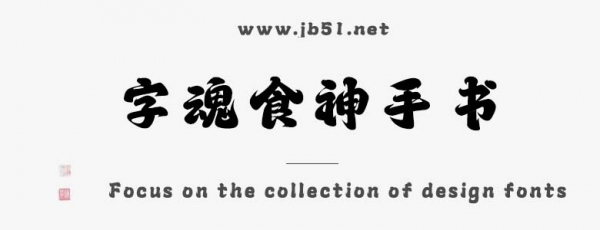
字魂食神手書是由字魂字庫推出的創(chuàng)意字體,該包含9503個中文、字母、 符號和數(shù)字,具有力量的風(fēng)格,可以滿足您設(shè)計上的各種需求,適合應(yīng)用于藝術(shù)設(shè)計、平面宣傳設(shè)計、網(wǎng)頁設(shè)計,書法字帖等領(lǐng)域。
字魂食神手書字體是一款商用的創(chuàng)意書寫字體,該字體包含9503個中文、字母、 符號和數(shù)字,具有力量的風(fēng)格,可以滿足您設(shè)計上的各種需求,該字體主要用于標題等場景, 您不但可以在字魂網(wǎng)下載字魂食神手書字體,同時還有眾多毛筆書法字體、創(chuàng)意字體等可供選擇!